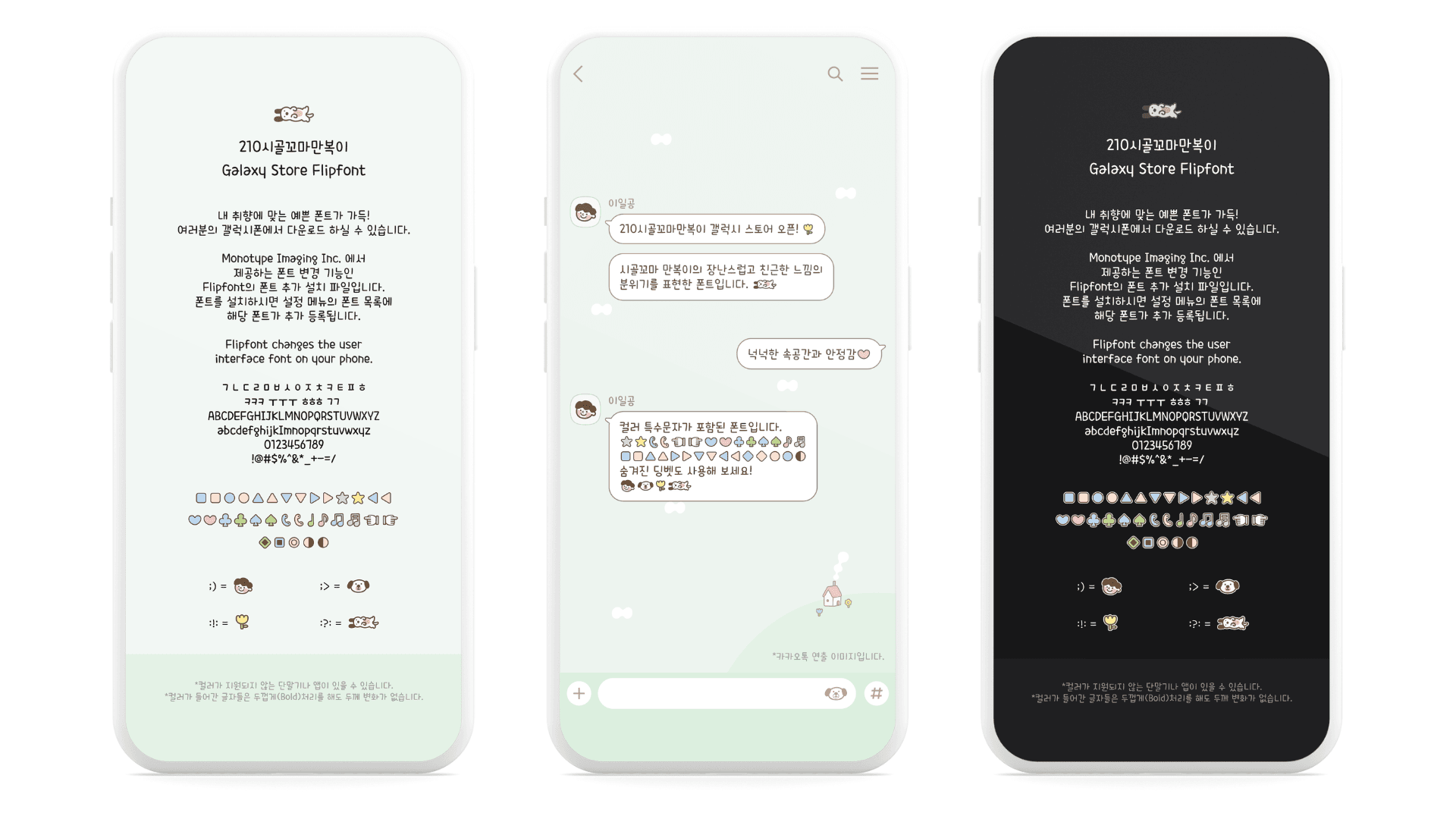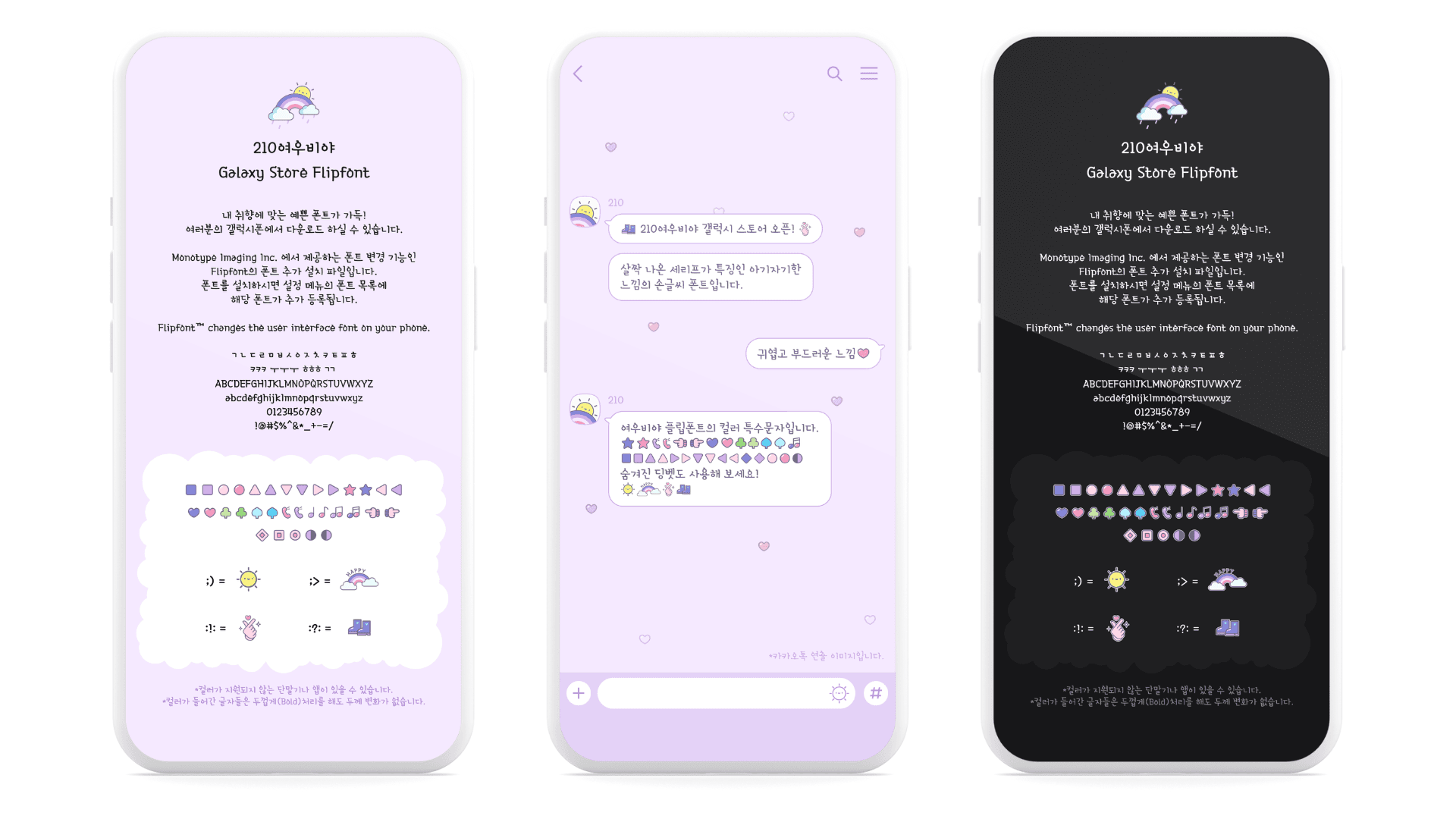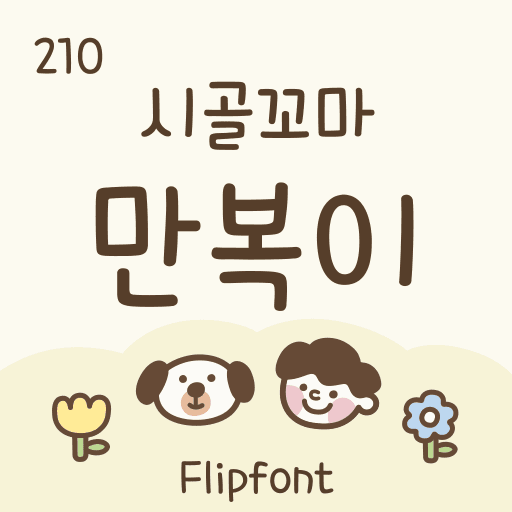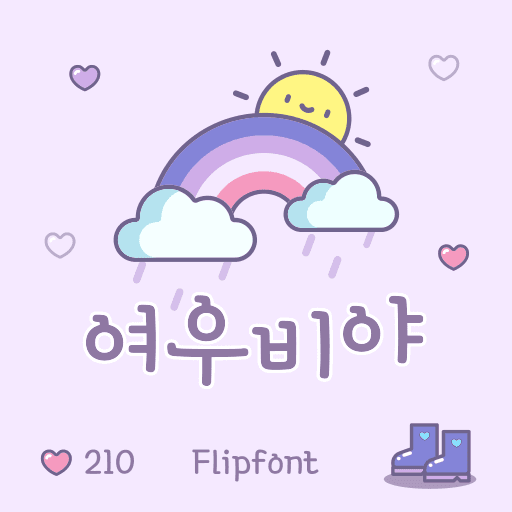
장난기 가득하고 다정한 무드를 담은 폰트예요. 자연스럽게 이어지는 선과 부드러운 마무리가 편안한 분위기를 주고, 큼직하게 디자인된 초성은 귀엽고 발랄한 매력을 더합니다. 꽉 찬 모듈 구조 덕분에 속공간이 넉넉하고, 문장을 조합했을 때 안정적인 흐름을 만들어 다양한 디자인에 활력을 불어넣습니다. 지금 바로 210시골꼬마만복이로 내 휴대폰에 유쾌한 에너지를 더해보세요!
작은 세리프가 톡톡 튀는 포인트가 되는 손글씨 스타일 폰트예요. 라운드 처리된 자소 덕분에 귀엽고 따뜻한 분위기를 주고, 리듬감 있게 이어지는 글줄은 경쾌하고 발랄한 매력을 더해줍니다. 내 휴대폰에 아기자기한 생기를 불어넣고 싶다면, 지금 바로 210여우비야를 만나보세요!